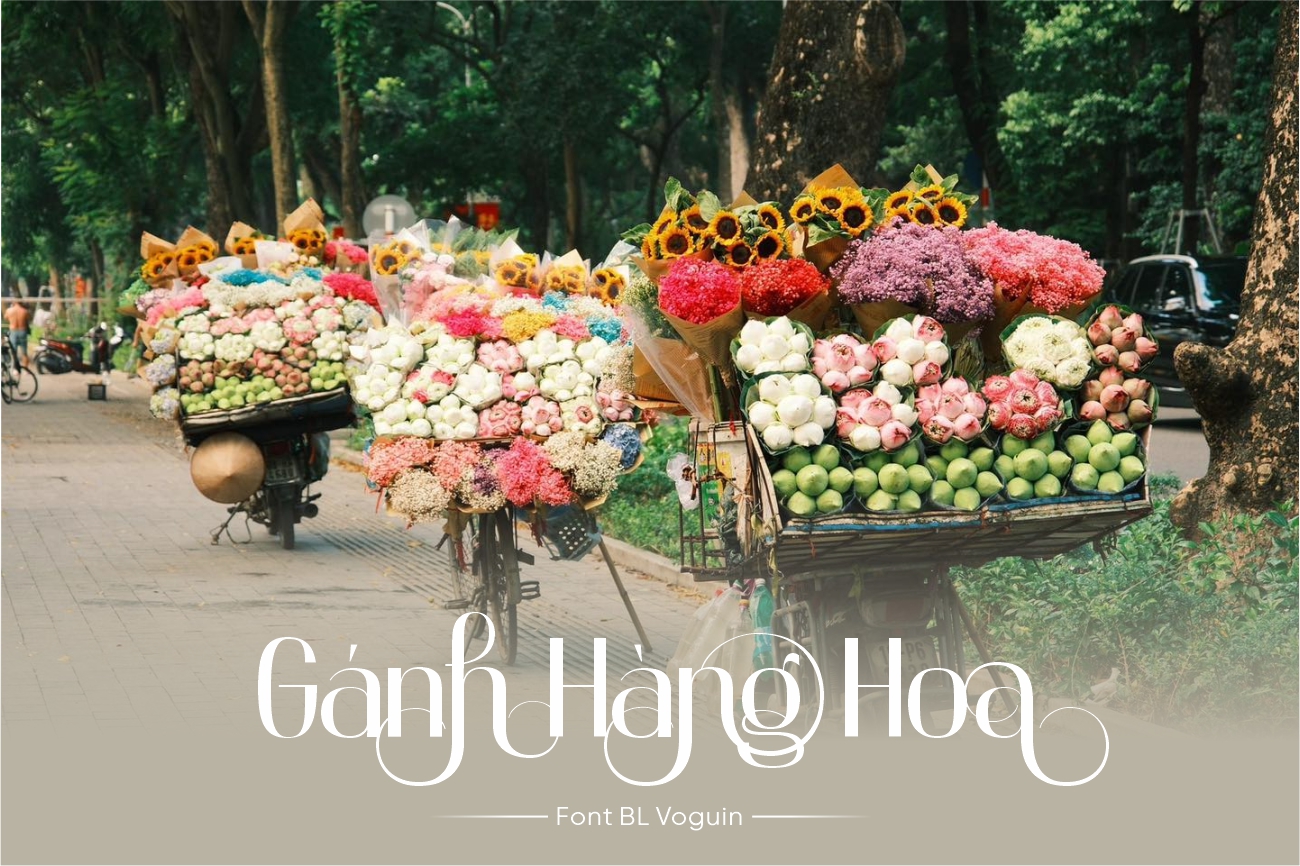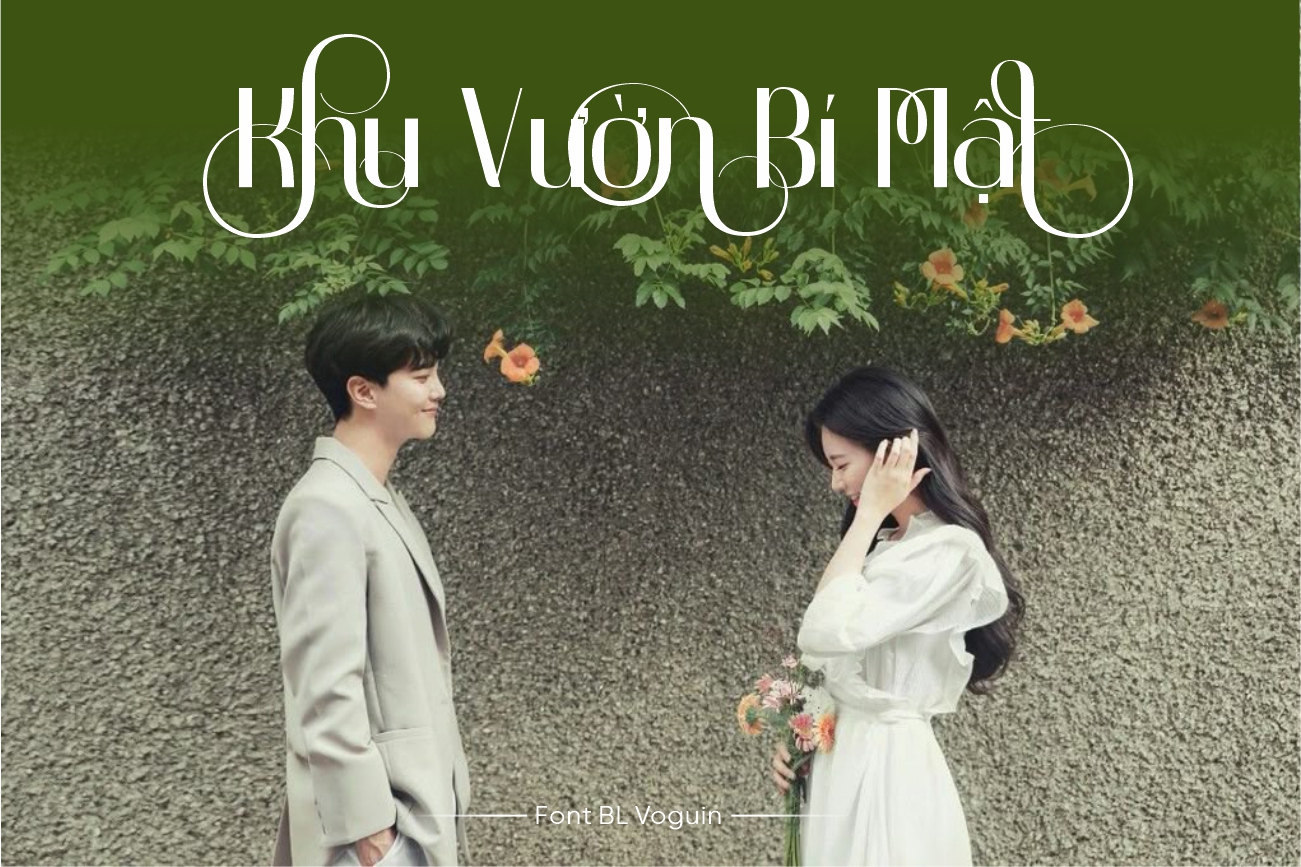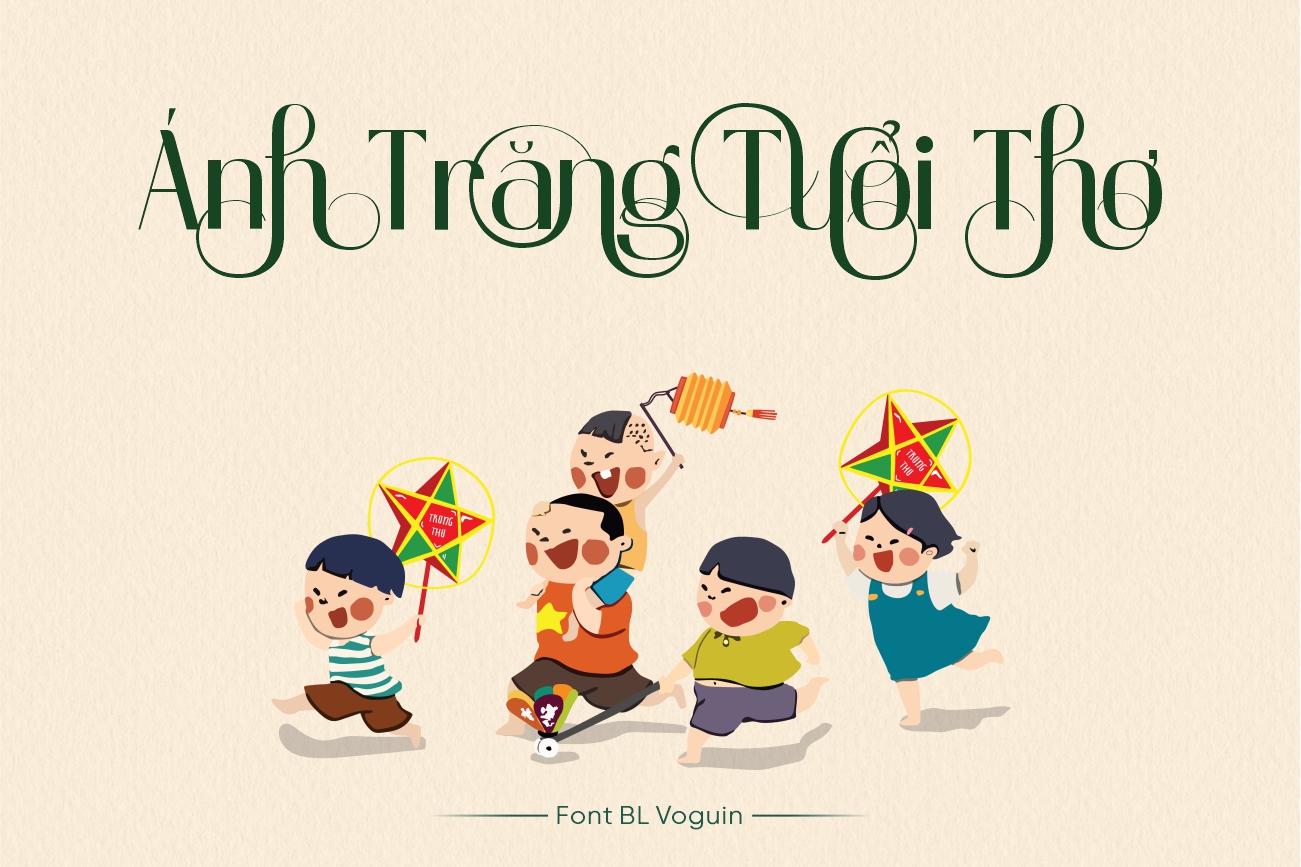
Font chữ uốn lượn Việt hóa đầy tinh tế - BL Voguin
Trong thế giới thiết kế, font chữ luôn là yếu tố quan trọng để tạo nên sự khác biệt và truyền tải cảm xúc thị giác. Một trong những lựa chọn nổi bật hiện nay chính là BL Voguin, phiên bản Việt hóa từ font gốc Voguin, được bổ sung đầy đủ dấu tiếng Việt và tối ưu hóa cho người dùng trong nước. Đây là một font chữ uốn lượn đầy tinh tế, mang lại nét đẹp sang trọng, lãng mạn và vô cùng cuốn hút.
Font BL Voguin được đặc trưng bởi những đường cong mềm mại, các nét chữ uốn lượn đầy nghệ thuật kết hợp với cấu trúc serif thanh thoát. Sự pha trộn giữa nét dày và nét mảnh tạo nên hiệu ứng thị giác mạnh mẽ, giúp chữ cái trở thành một phần của tác phẩm nghệ thuật chứ không đơn thuần chỉ là công cụ hiển thị văn bản. Nhờ đó, BL Voguin trở thành lựa chọn hoàn hảo cho các dự án thiết kế logo, typography nghệ thuật, poster thời trang, bìa tạp chí hay các ấn phẩm mang phong cách cổ điển xen lẫn hiện đại.
Điểm đặc biệt của font chữ Việt hóa này chính là hệ thống dấu tiếng Việt được xử lý tỉ mỉ, đảm bảo sự cân đối và hài hòa với tổng thể chữ cái. Người dùng hoàn toàn có thể yên tâm khi áp dụng vào các dự án cần nội dung tiếng Việt, từ các slogan ngắn gọn cho đến tiêu đề nổi bật trong thiết kế in ấn hay digital.
Không chỉ mang lại tính thẩm mỹ cao, BL Voguin còn khơi gợi sự sáng tạo cho nhà thiết kế nhờ bộ glyph phong phú cùng nhiều tùy chọn ligature và swash uốn lượn. Chính điều này đã giúp font trở thành công cụ đắc lực để tạo nên những tác phẩm mang dấu ấn riêng biệt, khác biệt so với những phông chữ thông thường.
Nếu bạn đang tìm kiếm một font chữ uốn lượn vừa sang trọng, vừa phù hợp với ngôn ngữ Việt, thì BL Voguin Việt hóa chắc chắn là lựa chọn lý tưởng để nâng tầm thiết kế.